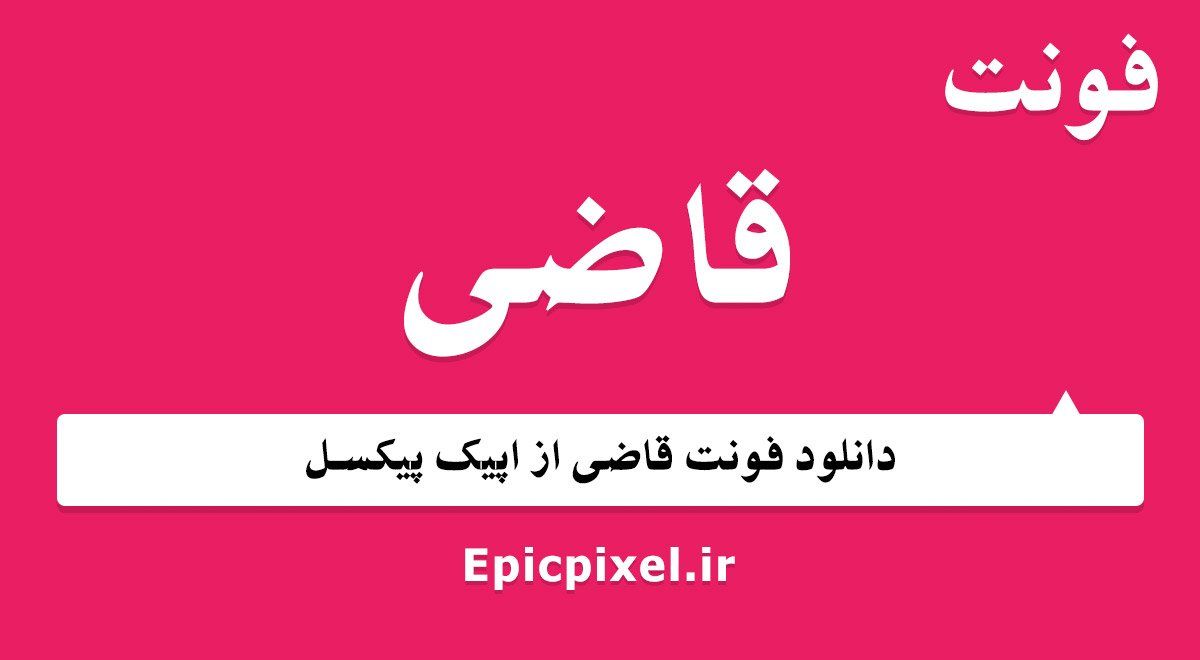
فونت قاضی عربی فارسی
فونت قاضی، با طراحی خاص و منحصربه فردش، حس اقتدار و جدیت را به نوشته های شما می بخشد؛ این فونت با خطوط استوار و فرم های خوانا، در عین حال که ظاهری رسمی و قاطع دارد، از زیبایی و ظرافت خاصی نیز برخوردار است. اگر به دنبال فونتی هستید که در طراحی های حقوقی، اداری، یا هر متنی که نیازمند حس اعتبار و اطمینان است، استفاده کنید، فونت قاضی گزینه ای ایده آل خواهد بود.
این فونت با ساختار قوی و حروف خوش فرم خود، تأثیرگذاری متن را افزایش داده و به آن جلوه ای ویژه می بخشد؛ فونت قاضی با ارائه ترکیبی مناسب از استحکام و زیبایی، به نوشته های شما شخصیتی متمایز می بخشد و باعث می شود متن شما در میان سایر متون، برجسته و چشمگیر باشد.
به عنوان مثال، تصور کنید در حال طراحی یک پوستر برای یک همایش حقوقی هستید؛ فونت قاضی با ایجاد حس اعتماد و اعتبار، به مخاطب القا می کند که موضوع همایش جدی و مهم است. یا در طراحی سربرگ یک نامه اداری، این فونت با ظاهر رسمی خود، حس حرفه ای بودن و دقت را منتقل می کند. پس اگر می خواهید نوشته هایتان قدرتمند و تأثیرگذار باشند، فونت قاضی را از دست ندهید. این فونت به صورت رایگان در دسترس است و می توانید به راحتی آن را دانلود و استفاده کنید.